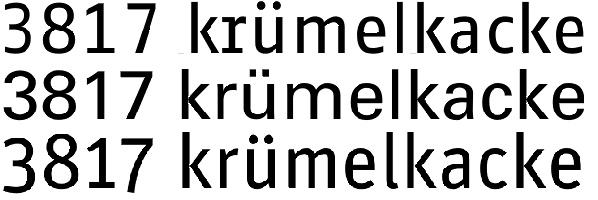
Schrift für kleine Schriftgrade
Frage an die Schriftexperten: Ich brauche eine im Ausdruck hervorragend lesbare(!),
trotzdem platzsparende Schrift mit 9 bis max. 10 Punkt. Einsatz: Viel Tabellentext
(Excel) mit etwas weniger Ziffern. Es entfallen nach Probedruck u. Leseeindruck
mehrerer Personen u. a. : Unit, Fago, Axel, Milo, Stones, Helvetica.
Auch die Vectora ist in der Größe überraschend schlecht lesbar ("Augenpulver").
Die Anselm Sans käme dem schon näher, ist aber auch nicht optimal.
Wäre für hilfreiche Vorschläge dankbar. Im Druck sieht das immer ganz anders aus
als auf dem Monitor.
Die Anselm Sans käme dem schon näher, ist aber auch nicht optimal.
Nur aus persönlichem Interesse: Warum nicht? Ist das Geschmack oder hat das einen technischen Grund?
ich empfehle für sowas die axel, habe ich sehr gute erfahrungen gemacht.
Axel: Habe ich, ist aber für 8 bis max. 10 Punkt mit viel Text zu klein/eng/schlecht lesbar.
Anselm Sans: Wirkt mit viel Text zu unruhig. So der Eindruck mehrerer Personen. Vielleicht Geschmackssache.
Eine Schrift kommt der Sache näher: Mentone, die könnte evtl. passen.
Wäre trotzdem für weitere Anregungen dankbar, denn ich arbeite viel mit solchen Schriftgrößen
u. möchte mir dafür mal eine wirklich passende Schrift kaufen.
… möchte mir dafür mal eine wirklich passende Schrift kaufen.
Das liegt nicht nur am verwendeten Font, sondern auch am Zeilenabstand, an der Zeilenbreite, am Satzspiegel, an der Fontfarbe, am Seitenformat, am Spaltenabstand, an der Spationierung und so weiter und so fort.
Gute Lesbarkeit nur am Font festzumachen finde ich etwas gewagt. Ein toll geeigneter Font in einem schlechten Layout ist schlimmer als ein halbwegs passabler Font in einer für die Lesbarkeit perfekten Umgebung.
Wenn Du Probleme mit den von Dir genannten Schriften hast, würde ich vielleicht erst mal einen Blick auf das Layout an sich werfen, bzw. wie deine Excel Tabellen aufgebaut sind. Lesbarkeit hat meist herzlich wenig mit der Schriftgröße zu tun, wie Bertel schon gesagt hat.
»Ein toll geeigneter Font in einem schlechten Layout ist schlimmer als ein halbwegs passabler Font in einer für die Lesbarkeit perfekten Umgebung.« Ich glaube, den Satz rahme ich mir im Büro mal ein. Super!
Magst Du uns vielleicht mal eine kleine »Kostprobe« hochladen?
Frage an die Schriftexperten: Ich brauche eine im Ausdruck hervorragend lesbare(!),
trotzdem platzsparende Schrift mit 9 bis max. 10 Punkt. Einsatz: Viel Tabellentext
(Excel) mit etwas weniger Ziffern. Es entfallen nach Probedruck u. Leseeindruck
mehrerer Personen u. a. : Unit, Fago, Axel, Milo, Stones, Helvetica.
Auch die Vectora ist in der Größe überraschend schlecht lesbar ("Augenpulver").
Die Anselm Sans käme dem schon näher, ist aber auch nicht optimal.
Wäre für hilfreiche Vorschläge dankbar. Im Druck sieht das immer ganz anders aus
als auf dem Monitor.
würde mich mal interessieren wieso unit, fago (n) und vectora rausfallen?
9–10 pt ist ja nun auch kein augenpulver. und ich habe mit der fago n selbst in 5 pt
schon lesbare ergebnisse erzielt.
erst neulich habe ich die national book auf 5 pt gesetzt (4-farbiger offsetdruck) und sie
war gut ziemlich lesbar, was mich selbst etwas überrascht hat. ok, es waren nur 2 kleine
zeilen, auf die dauer will man ja sowas nicht lesen.
nutzt du einen tintendrucker für deine testausdrucke?
Statt der National wären vielleicht auch Tannenberg, Deutschland, Element, Potsdam usw. eine Überlegung wert.
Also zunächst: Nehmt mir meine etwas laienhaften Bemerkungen bitte nicht übel.
Mir geht es bei dichtbeschriebenen Excel-Tabellen (A4 + A3 als Tinten- u. Laserdruck)
stets nur um optimale Lesbarkeit, bei viel Text mit Ziffern meist nur in 8-10 Punkt.
Ich möchte im Alltag auch nicht jeweils ständig die Schrift anpassen müssen (Laufweite etc., was in Excel auch nicht besonders zeitsparend geht).
Bestes Lesbarkeitsergebnis in 9 Punkt war bisher mit Univers. Die anderen genannten Schriften (Unit, Fago, Vectora) sind alle prima, aber in 9 Punkt war das Ergebnis für mehrere neutrale Personen nicht so überzeugend, allenfalls noch mit Unit.
Dank für Eure Geduld u. weitere hilfreiche Schrifthinweise, die ich mit Sicherheit ausprobieren werde.
Die Schrifthinweise von Joshua K. sind sicher ein kleiner Scherz.
Womöglich wird die Lesbarkeit einiges besser, wenn Du den Schriftgrad auf etwa 6 bis 7 Punkt reduzierst, dafür dem Ganzen etwas mehr Luft lässt: Weissraum schaffen, auf unnötige Linien (vor allem die vertikalen) verzichten, usw.
Die Frutiger ist zwar nicht besonders originell, aber halt schon sehr gut lesbar in den kleinen Graden. Fago geht meiner Meinung nach gar nicht.
Warum nicht die einst fürs Telefonbuch-Augenpulver konstruierte Bell Gothic mal wieder hervorkramen?
@Hansa
Anstatt des "Neutrums" Univers die Trade Gothic? Auch wegen der von Robert bemäkelten Ziffern.
Akkurat ist auch fein, wenn nur eine Breite und wenige Schriftschnitte gebraucht werden.
Frutiger? Gar die Myriad? Kievit?
Eure kontroversen Beiträge sind immer wieder bereichernd.
Fago, Axel, Unit – sorry, alles leider nix in 9 Punkt (jedenfalls nicht ohne techn. Änderungen)
Gerade ausprobiert - brauchbares Ergebnis: Stone Sans u. Museo Sans, ggf. Trade Gothic.
Am besten lesbar immer noch: Univers, nur die Ziffern sind natürlich nicht optimal.